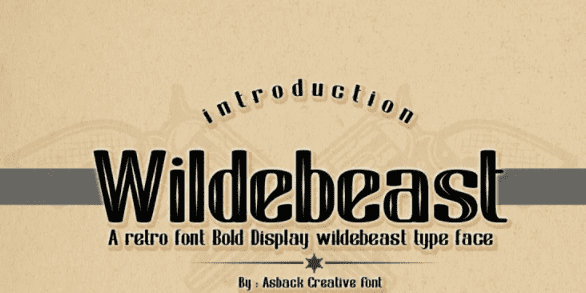
[Fontbundles] Wildebeast Font (2021)
Название: Wildebeast Font (2021)
[Fontbundles] Wildebeast Font (2021)
Wildebeast - это тип ретро-шрифта с классической и характерной формой, которая придает ощущение старой школы в нем с добавлением комбинации каждой буквы, дающей дополнительное впечатление для многих ваших проектов есть много вещей, которые вы можете сделать с этим шрифтом, а именно вы можете использовать его в качестве названия романа книги, классического названия фильма и ваших классических историй в социальных сетях.